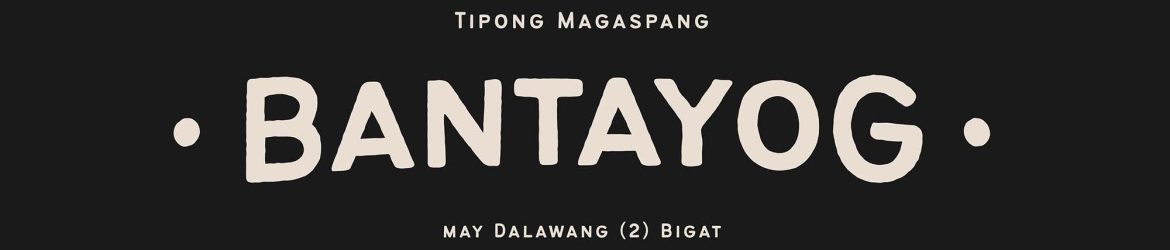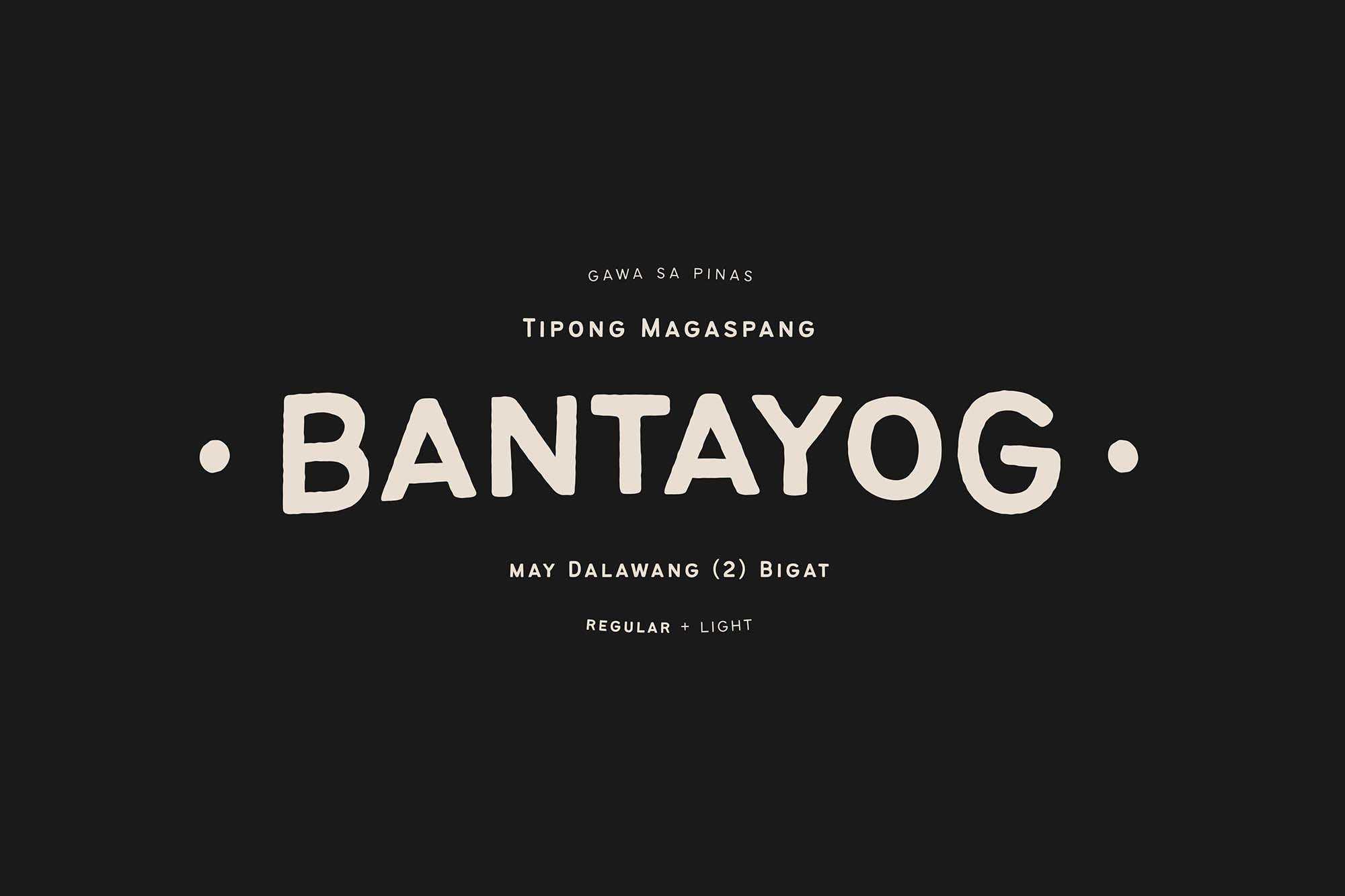
Bantayog Rough Typeface
Através de seu design antológico e contornado com as letras Bantayog Rough Typeface, você tem a oportunidade de desafiar as expectativas e criar designs que chamem a atenção. Essa tipografia não é apenas para quem busca um design suave e simples, mas para aqueles que querem uma mudança, um toque de desafio. Cada letra neste tipo de fonte traz uma nova perspectiva, um toque inovador que pode ser a resposta certa para os desejos de qualquer cliente. Se você está procurando algo que se destaque e surpreenda seus espectadores, esse é o recurso para você. Seja para um site, um livro ou qualquer projeto de design, essa fonte vai dar um toque único e impactante.